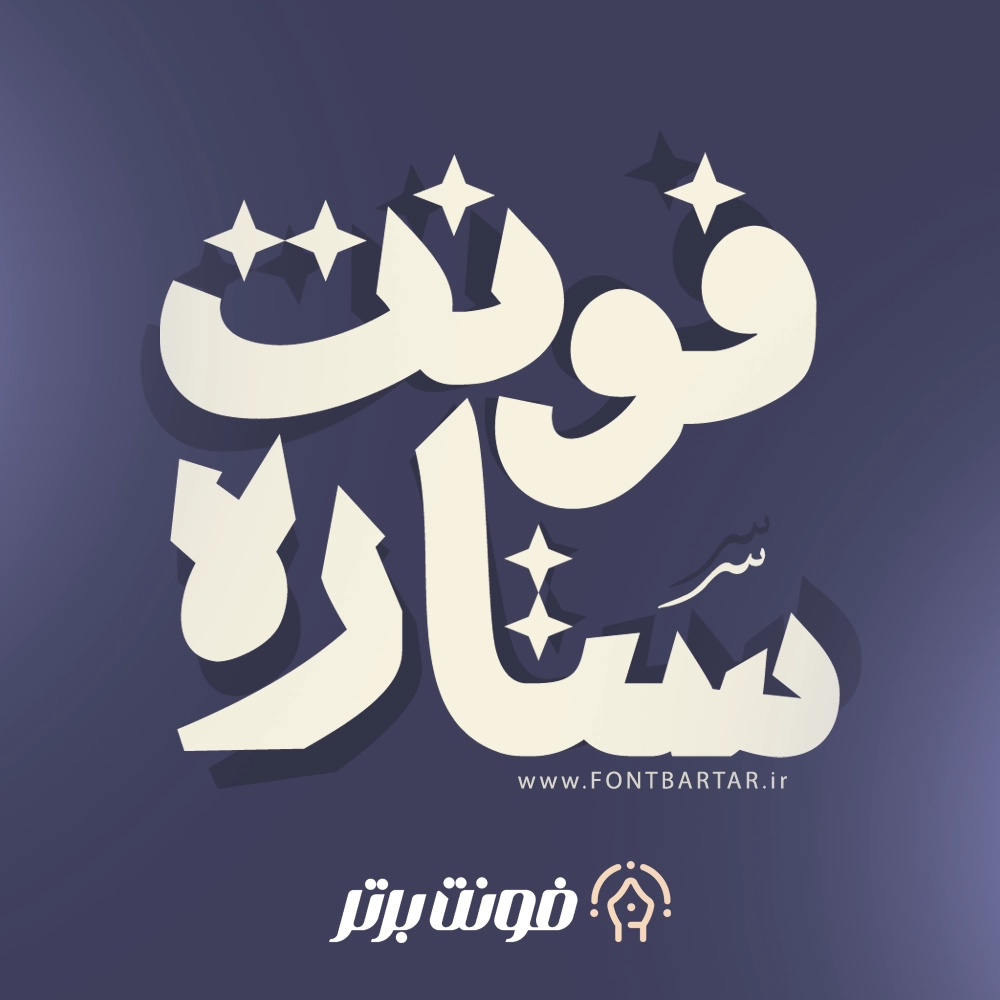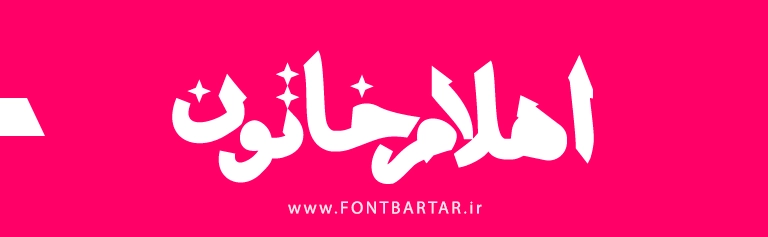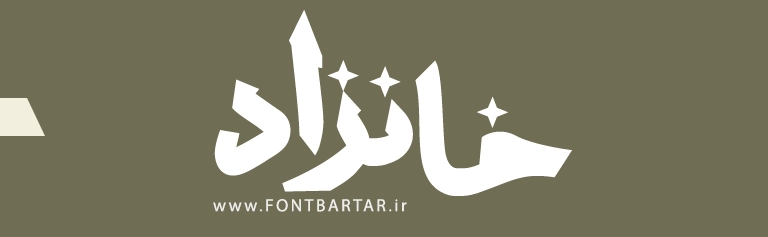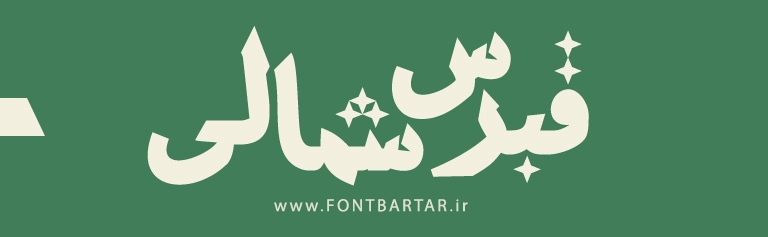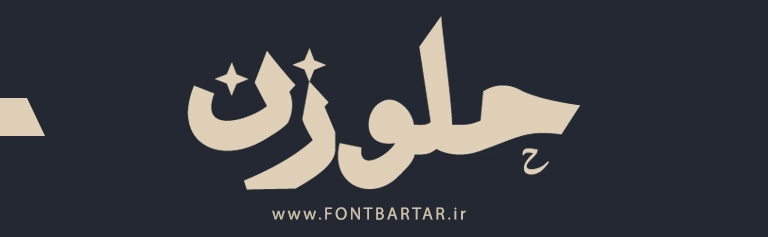
دانلود فونت ستاره – فونت فانتزی و خاص برای طراحیهای خلاقانه
فونت جدید ستاره یکی از جذابترین و خلاقانهترین فونتهای فانتزی فارسی است که با طراحی منحصربهفرد، حالت نرم و خطوط گرد، مناسب انواع طراحیهای مدرن و گرافیکی میباشد. این فونت جدید فارسی با وجود المانهای ستارهای و طراحی خاص خود، برای لوگوتایپسازی، طراحی پوستر، کاور، بنر، تایپوگرافی و طرحهای شاد و کودکانه انتخابی ایدهآل است.
استفاده از این فونت به پروژههای شما روح، نور و جلوهای جذاب میبخشد و باعث میشود طرحهایتان نسبت به رقبا متمایز و حرفهای دیده شود.
ویژگیهای جذاب فونت ستاره
- طراحی فانتزی همراه با المانهای ستارهای
- مناسب برای لوگوتایپ، پوستر، کاور موزیک، کارتونی و طرحهای کودکانه
- فونت جدید ایرانی پشتیبانی کامل از حروف فارسی
- مناسب گرافیستها، طراحان محتوا و طراحان لوگوتایپ
- فونت جدید استوری خوانایی بالا با وجود سبک فانتزی
- مناسب صفحات مناسبتی، تبلیغاتی و طرحهای مرتبط با جشنها
فونت زیبا ستاره مناسب چه کسانی است؟
اگر یک طراح هستید و به دنبال فونتی میگردید که در یک نگاه، توجه مخاطب را جلب کند و جذابیت بصری پروژهتان را افزایش دهد، فونت زیبا فارسی ستاره بهترین انتخاب شماست.
- طراحان گرافیک
- تولیدکنندگان محتوا
- طراحان جلد کتاب و کاور
- طراحان پوستر و بنر مناسبتی
- سازندگان لوگوتایپ فانتزی
- صفحات کودک و نوجوان
۱. فونت ستاره برای چه نوع طراحیهایی مناسب است؟
این فونت برای لوگوتایپ، پوستر، کاور موزیک، طرحهای کودکانه و طراحیهای فانتزی بهترین انتخاب است.
۳. خوانایی این فونت در سایزهای کوچک چگونه است؟
با وجود طراحی فانتزی، این فونت در سایزهای متوسط و بزرگ بهترین عملکرد را دارد و خوانایی خوبی دارد.